字体下载大全很多,让我们在工作和学习中觉得难以选择,而且几乎都用过,所以也就不觉得哪种字体比较好。但我们拥有一套属于自己的、特殊的字体是真的重要,所以可爱的字是我们一个不错的选择。选择自己喜欢的字体,让他人看起来更加具有文化浓郁的味道,是一个优秀学者必备的风范。
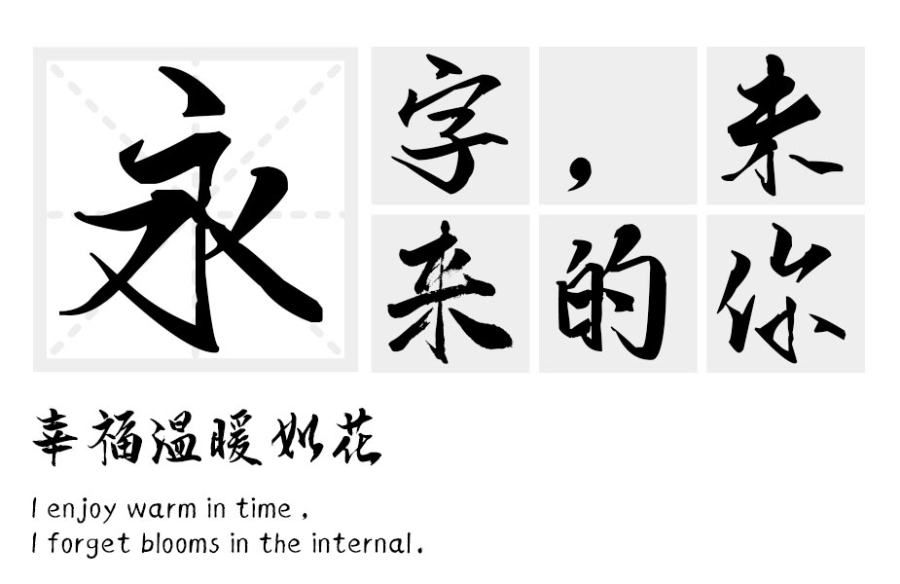
可爱,顾名思义就是看起来特别让人喜欢的感觉,看起来就很不一样,字体视界中的它具有一种能够让人一眼就看上的魔法。可爱的字多数就是会有文字和图片搭配,通过在漂亮好看的字体上面写上符合情景的配文,并把配文加以修饰,上色换字体等等工序,字体视界里边的字体设计者通过大量的意见收集不断改进设计,设计出了特别好看并且与图片内容特别融洽的文字类型,可“俘虏”了很多少女的心呢。